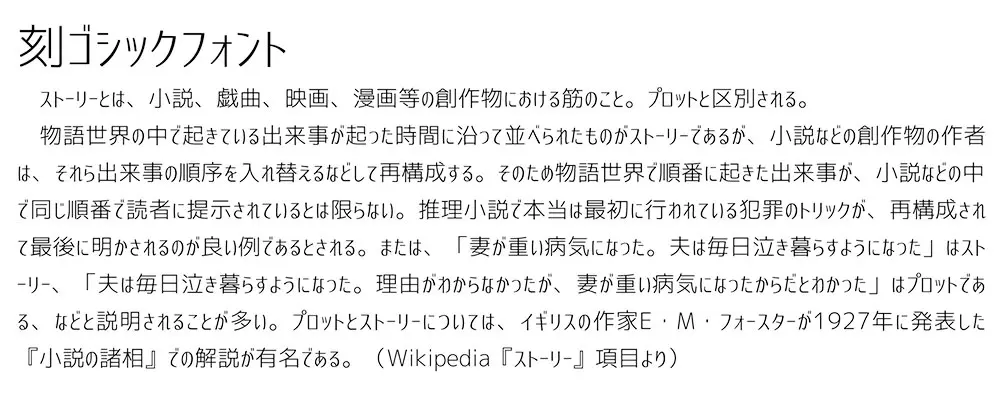
刻黑體(刻ゴシック)是一種結合了標準黑體字體與相矛盾的小平假名和片假名字符的字體。 與傳統的平假名和片假名相比,線性形狀是一個特徵。 漢字的設計水平圖像比垂直圖像略薄。 這表達了一種輕盈而有節奏的氛圍。
平假名和片假名保留其獨特的形狀,但不追求過於具體的設計,從而帶來清新的效果。 合理平滑的曲線給人一種安全和穩定的感覺。 雖然假名與一般字體有很大不同,但它的設計目的是保留每個識別字符的特性,以免降低可讀性。